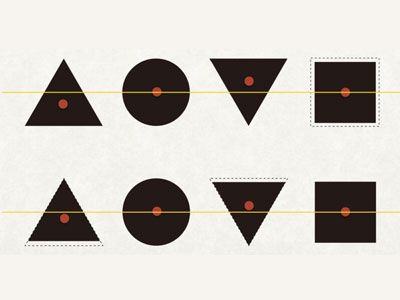
跟我学字体:中文字形的重心
当我们使用中文字型时,横排是最基本的排版方式。但你可能不知道,正在阅读的这些中文字之所以横排时阅读顺畅,没有特别的违和感,都是字体设计师历尽千辛万苦调整后的成果。
反过来说,如果设计中文字型不注意,忽略一些设计原则,那么阅读起来就会有忽高忽低,遇到乱流的感觉。我们看一下下面这个案例:
以金梅歪体美工国际码为范例,这个字体存在的问题实在是太多了,现在我们先着重看文字重心的部分。大家可以实际阅读看看,第二行出现的「不太平衡」这四个字应该可以非常明显地重心的不平衡吧?
大概像这样:不↑ 太↓ 平↑ 衡↓
如果有好好调整过文字重心的话,阅读起来就会顺畅许多:
为什上面这段文字会阅读起来观感会如此不一样呢?我们这篇来好好谈一下文字重心:究竟文字重心是指「什么」的重心?如何判定每个文字的重心呢?
字体设计第一课:眼力训练
你能不能不靠工具测量,就看出观察几何图形之间谁大谁小,中间间隔又是否一致呢?其实这与测量数值无关,而与人眼的感受有关。
我在日本读研究生时,旁听了鸟海修老师帮设计系大一上的Typography必修课,第一堂课的课题就是几何图形的调整练习。什么?几何图形的调整跟字体设计有关?也许说了你才会惊觉,△◯▽□可以分别对应到拉丁字母的“AOVH”字母的外轮廓,也可以对应到中文字的“上永下国”的外轮廓。
是的,中文字也有轮廓。稍加观察后约能对应到15种甚至更多的几何图形,像是:方形、长方(站立)、长方(横躺)、圆形、正三角形、梯形、倒三角形、倒梯形、菱形、五边形⋯⋯等等。
在设计字体的时候,必须懂得判断出每个中文字大致对应到的几何图形。为什么这很重要?因为人眼有错觉。例如同样面积的菱形与正方形摆在一起,会觉得菱形硬是比正方形小了一点。以中文字来说,菱形的“今”与方块状的字例如“国”字摆在一起的时候,如果不把“今”字设计得大一点,很容易会以为这个字看起来比较小。先个别调整到合适的大小后,就要来面对重心、处理重心了。
重心的意思是:几何重心吗?
还记得初中教过图形的重心吗?正圆形与正方形的重心当然是在中心点的位置,而三角形的重心是这样找的:
假设今天我们要做的四个字是“上永下国”,那它们所对应到的图形如下:
首先正方形无论是面积或是视觉大小都太大了,需要稍微缩小一点:
接著我们用红点标出这些图形的重心,我们会发现三角形不调整几何重心不行,重心上下摆动太激烈了:
所以该如何调整呢?我们要改变三角形的底线摆位:
如此一来几何重心就会趋近一致,文字的阅读效果就会顺畅许多(无须调整至绝对一致,否则字会太小):
大家可以用电脑输入一些外轮廓明显不同的字,可观察出笔画的摆位有考量到几何重心,其实“上”“下”“国”三字是展开一套新字体设计时蛮重要的基准字,无论是几个字的标准字设计,或想延伸造出一套几千字的字库都建议优先制作这三个字,这样一来就能定义出一些很重要的参考线与框架,想了解更多的话,可以参照我们在金萱家族设计细节裡提到的“字形调整框”:
不过,光是外轮廓的笔画摆位恰当就足够了吗?何谓视觉重心呢?
其实,影响我们阅读文字时的高度观感不单是上面所提到的文字外轮廓与几何重心而已,就算是框架一样但透过文字笔画的摆位不同,也可以做到改变文字的重心。一样的框架设定下,若藉由笔画的长短变化营造出不同的文字重心,看起来就会像下面这样:
文字重心是一种经过训练的视觉感受
所以说影响我们对于一个文字重心高低的观感不单只有外轮郭及几何重心,还包括所有笔画的摆位(文字结体)的影响,综合之后会产生一个文字的「视觉重心」,视觉重心的一致才是我们调整文字重心时的目标。
视觉重心的确有点抽象,是一种感受而并没有一个确切的点,需仰赖设计师造字经验累积后所磨练出的眼力,以及多将自己所造出的字,进行各种尺寸与不同排列组合的排版测试,才能察觉到重心的偏移异状并加以调整。
让我们一起加油吧,设计师朋友们~这是一条漫长的练字之路。
题外话:为什么我看了那么多字,也写了那么多字,却没留意过中文字有重心这回事呢?
最主要的原因是由于我们日常生活中所见所使用的内建字型,都已经是花费人力经年累月的经验与调整下的成果了。只要是字体公司出产的字库,都已针对横排与竖排的排版需求细心调整过不同文字的重心,让读者横排阅读时不会忽高忽低,直排阅读时不会忽左忽右。
此外“书写”跟“设计”中文字两者在构筑骨架时与最后取得平衡的方式不太一样。对书法与文字造型有长期钻研的艺术家徐冰这样说过:
“书写一个中文字时,所下的每一笔都被前一笔所影响,必须灵活的改变笔的角度与调整位置,而最后一笔最终平衡了整个字。”
我蛮认同这个说法的,其实我们在进行书写时,都没有意识到自己正在进行微妙的视觉调整呢。
重心不同也是一种风格的表现方式
字型要能够阅读,重心稳定是很基本的要求。但如果对字的要求不是易于阅读文章,而是强调风格表现,我们也依样可以从重心下手营造特殊的美感。
新艺术运动(Art Nouveau)的著名设计师 Rennie Mackintosh 所设计的字体,就是利用特意拉高文字重心,营造出独特的张力与风格:
台湾设计师廖小子透过高重心的文字设计,营造紧张与恐怖的气氛